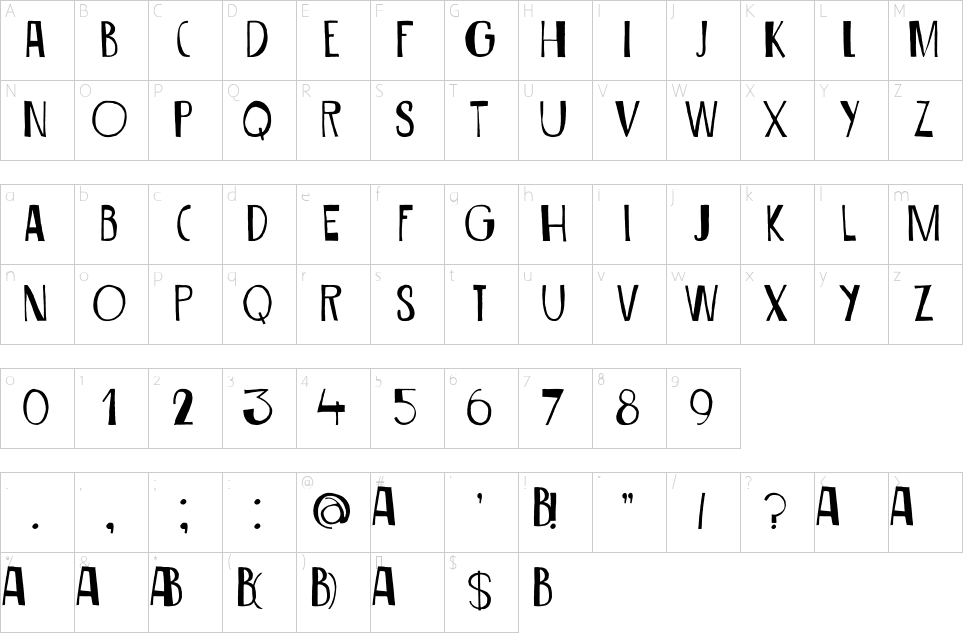
A DK Sirius B é uma fonte elegante projetada por Hanoded que se destaca entre as demais com seu estilo moderno e fluido. Esta fonte foi desenhada para oferecer um contraste interessante, tornando-a perfeita para uso em design gráfico de alta qualidade, desde editoriais até marcas corporativas. Seu design cuidadosamente elaborado permite que seja usada tanto no Windows quanto Mac sistemas operacionais, garantindo uma experiência de uso fluida e acessível a todos. Com 1,906 usuários já baixando esta fonte gratuita, é claro que ela merece ser adicionada à sua coleção para enriquecer os seus projetos gráficos sem precisar pagar nada.